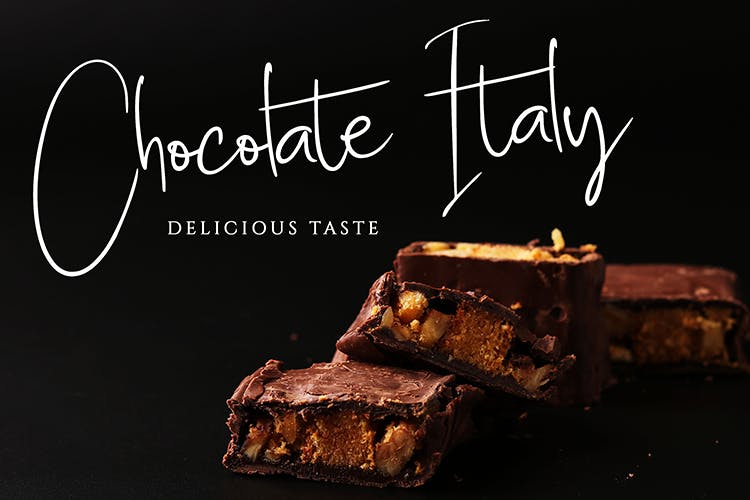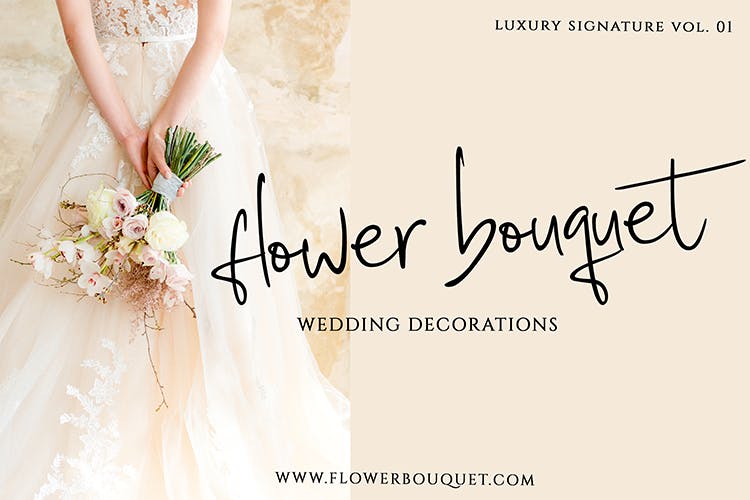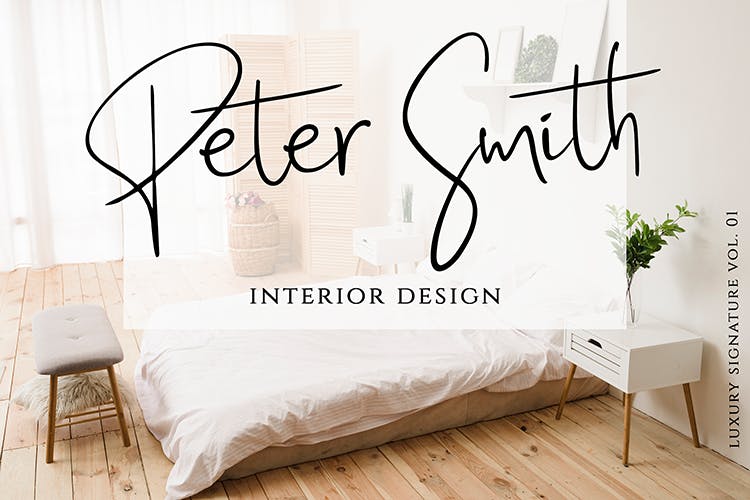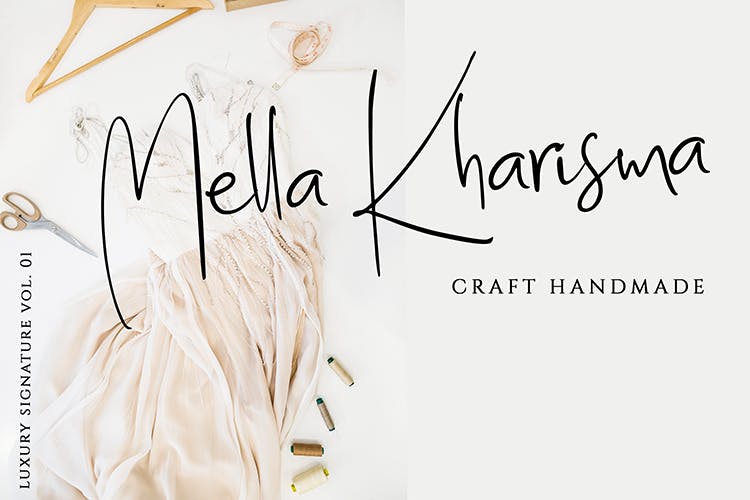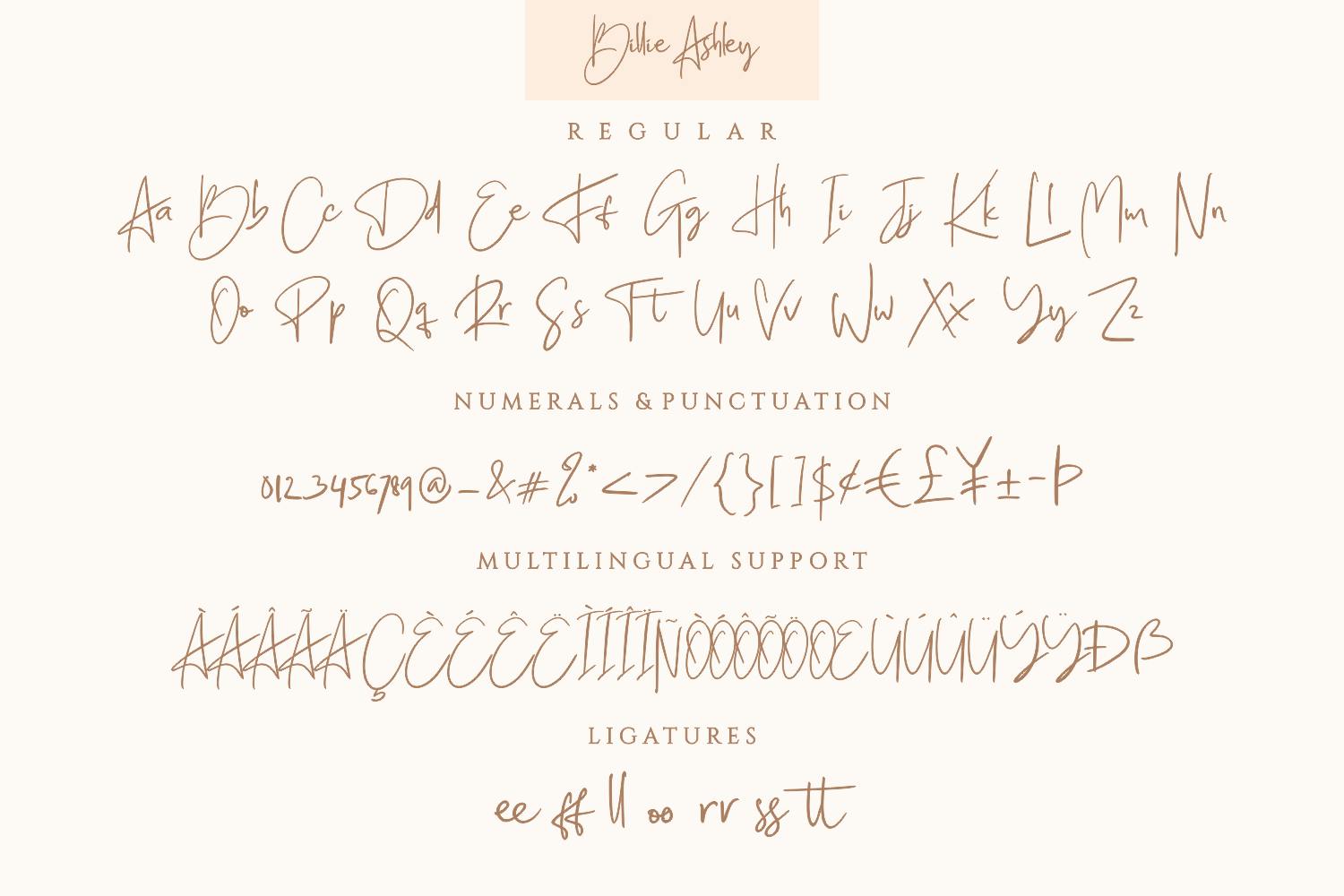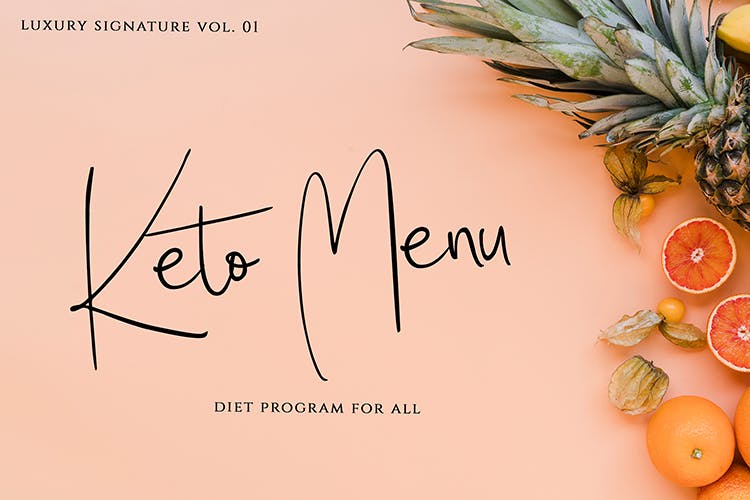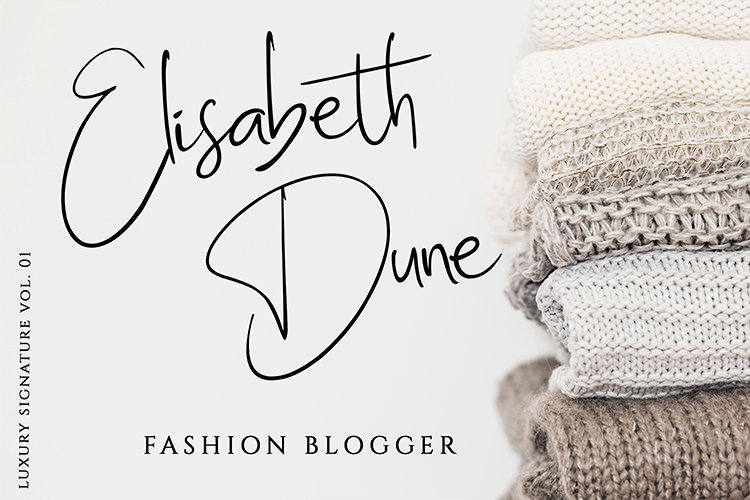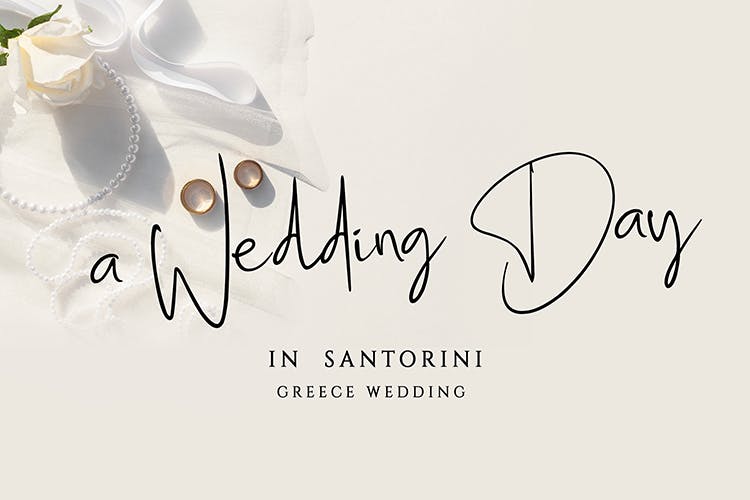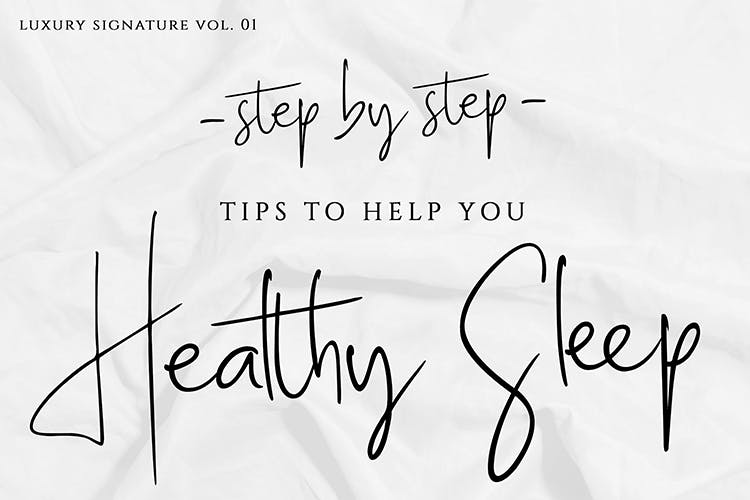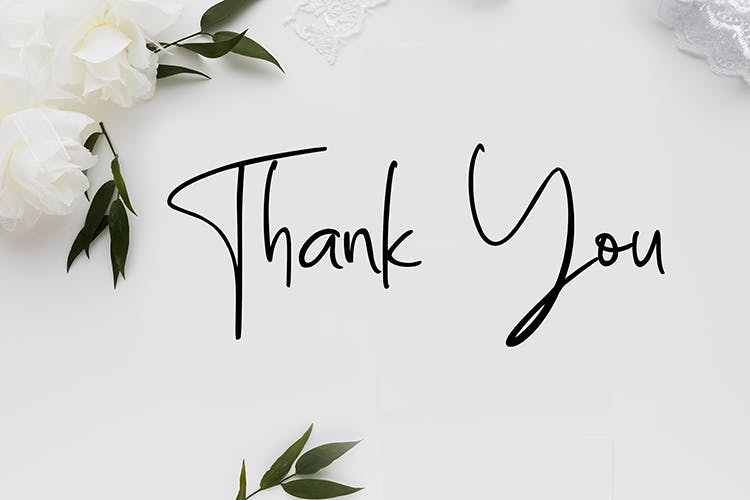
دانلود فونت امضای لوکس بیلی اشلی
Billie Ashley Luxury Signature Font
فونت دست‌نویس بیلی اشلی، انتخابی عالی برای طراحی‌های شما.
فونت دست‌نویس بیلی اشلی، یک فونت کالیگرافی شیک و مدرن است که به‌صورت دستی طراحی شده است. این فونت مناسب برای برندینگ، امضاها، دعوت‌نامه‌های عروسی و کارت‌ها و همچنین پروژه‌های دیگر می‌باشد.
فونت بیلی اشلی شامل تمام گلیف‌ها شامل حروف بزرگ، کوچک، اعداد، نشانه‌گذاری، چند زبانه و لیگاتور‌ها است.